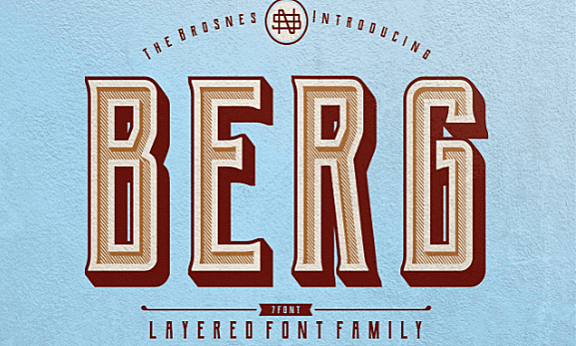
[系统字体] 分层复古字体 BERG字体 资源介绍参数 资源类别: 精美字体 如遇问题: 联系客服/留言反馈 下载地址: 前往下载 精美字体 21年1月19日 编辑 前往下载 喵容发布2号 取消关注 关注 私信 资源名称 BERG 资源大小 244mb 资源格式 ttf、png 资源简介 Berg包含一整套大写和小写字母,以及多语言支持,货币数字,数字和标点符号。 相关文章: [系统字体] 复古脚本字体:本文介绍的是一款具有复古外观的脚本字体——Buffalo。它是品牌和标志设计的理想选择,有需要的朋友可以到文末下载哦! 下载权限查看 ¥ 免费下载 评论并刷新后下载 登录后下载 查看演示 {{attr.name}}: 您 …... [系统字体]独特的复古字体—Coconut Inline Grunge:资源描述 字体 资源名称 独特的复古字体—Coconut Inline Grunge 资源格式 otf、ttf、jpg 资源大小 619kb 资源简介 这款字体适用于各种印刷项目,徽标,T恤,杂志封面,海报设计等。 可免费用于个人和商业用 …... [系统字体] 一款装饰性极强的字体——Moalang:今天分享的是一款装饰性非常强的一款字体——Moalang。它由印度尼西亚的字体设计师Agga Swist’blnk设计并且免费用于个人和商业用途! 喵容——Moalang字体1喵容——Moalang字体2 下载权限查看 ¥ 免费下载 …... [系统字体] 现代简约字体 PEENU字体:资源名称 PEENU 资源大小 279kb 资源格式 ttf、png 资源简介 Peenu是一种免费的大写字体,由印度年轻UI和平面设计师Nitish Kumar设计和发布。Peenu受Sharp Paper Cuts的启发,它是海报,传单,电影片头等制 …... [系统字体]优雅现代手写英文字体 Domillion字体:资源名称 Domillion 资源大小 591kb 资源格式 ttf、otf 资源简介 Domillion是海报,签名,标识,报价,专辑封面,名片,产品设计等的完美选择!该字体免费供个人使用! 喵容——Domillion-Brush-Font1喵容——D …... [系统字体]优质的装饰字体——Sabrva:资源描述 字体 资源名称 Sabrva 资源格式 ttf 资源大小 7.35kb 资源简介 Sabrva是完美字体的选择,可在 – 水印,签名,摄影,徽标,名片,报价,专辑封面使用。免费供个人使用! 喵容——Sabrva1喵容—— …... 喵容——BEGR字体1喵容——BEGR字体2 下载权限查看 ¥ 免费下载 评论并刷新后下载 登录后下载 查看演示 {{attr.name}}: 您当前的等级为 登录后免费下载登录 小黑屋反思中,不准下载! 评论后刷新页面下载评论 支付¥以后下载 请先登录 您今天的下载次数(次)用完了,请明天再来 支付积分以后下载立即支付 支付以后下载立即支付 您当前的用户组不允许下载升级会员 您已获得下载权限 您可以每天下载资源次,今日剩余次 声明:本文为原创作品,版权归作者所有。未经许可,不得转载或用于任何商业用途。如若本站内容侵犯了原著者的合法权益,可联系我们进行处理。 给TA打赏 共{{data.count}}人 人已打赏 BREG分层复古字体下载
好看 很复古
好看,很复古